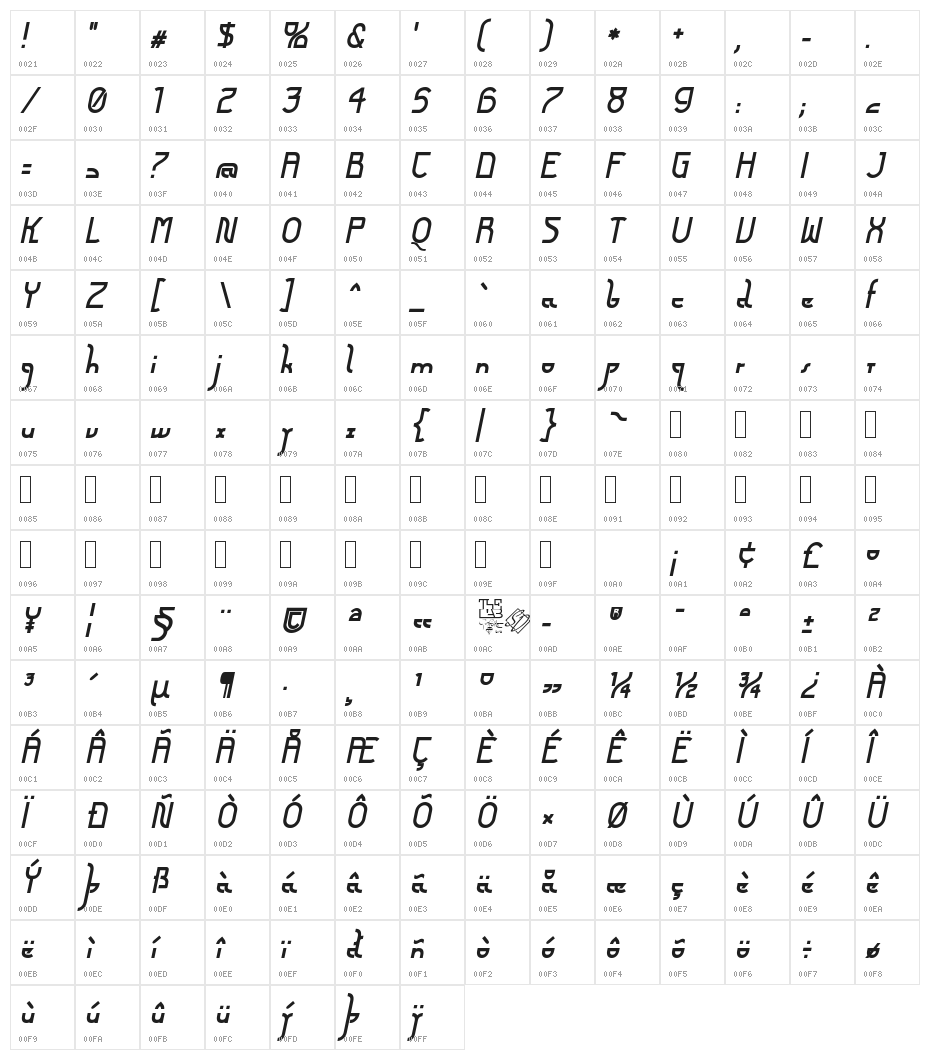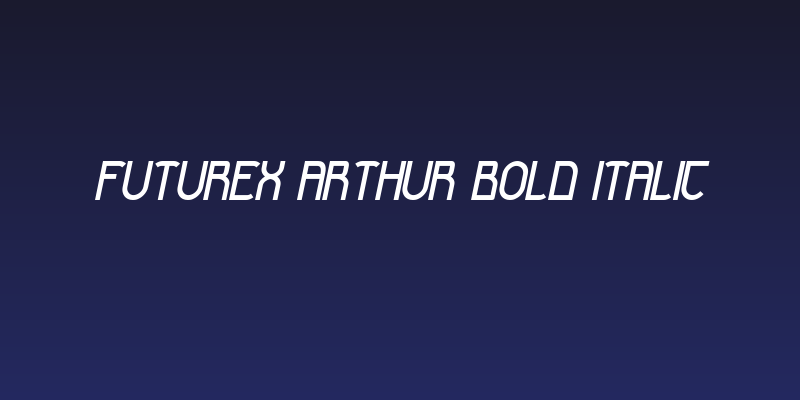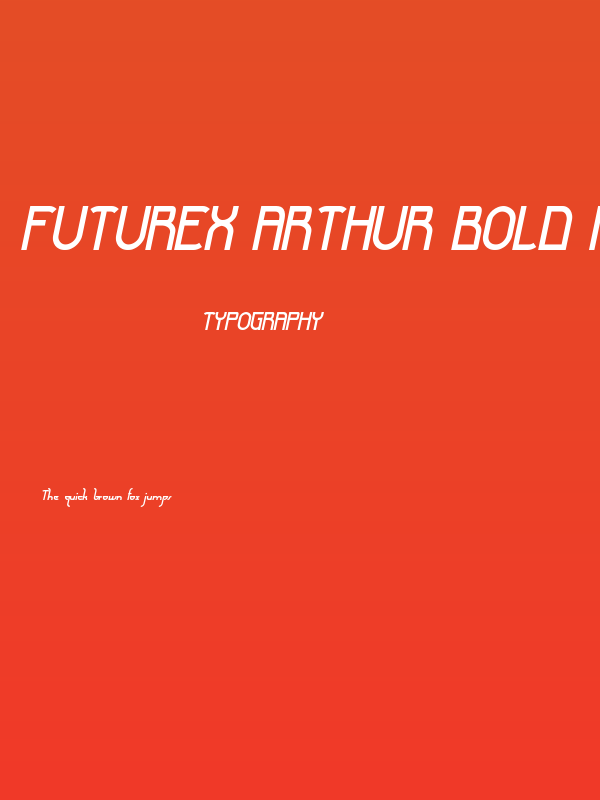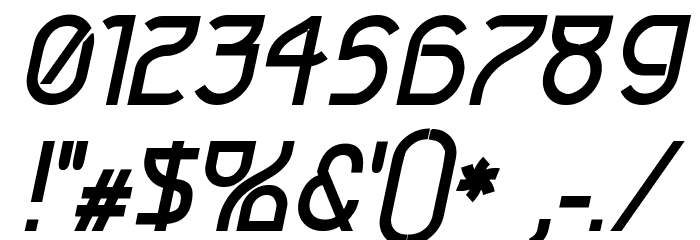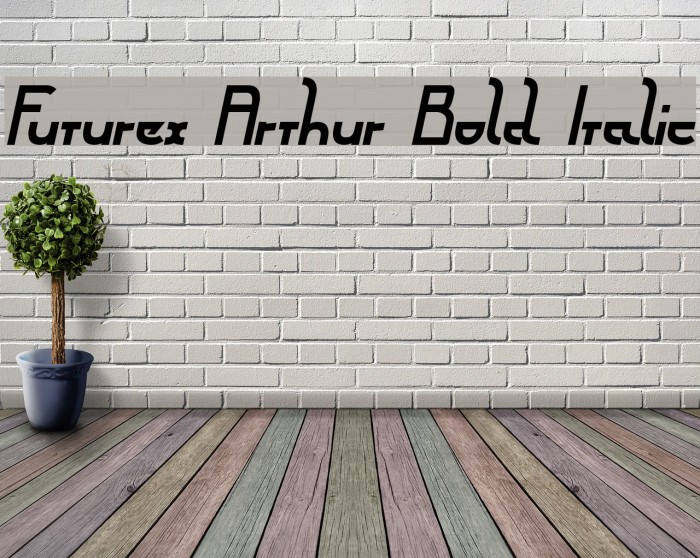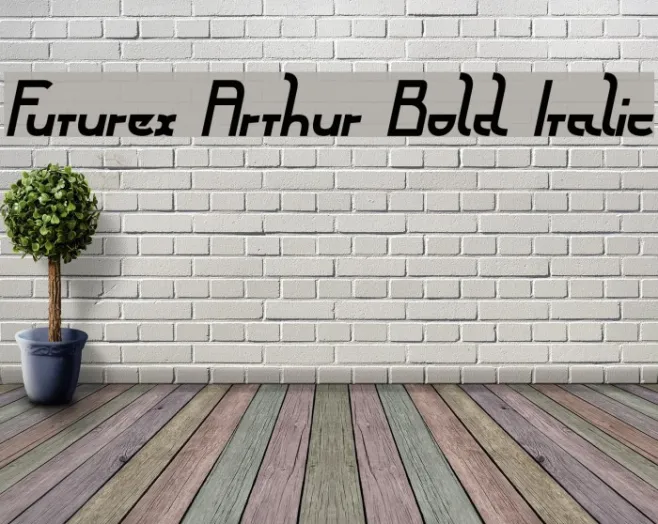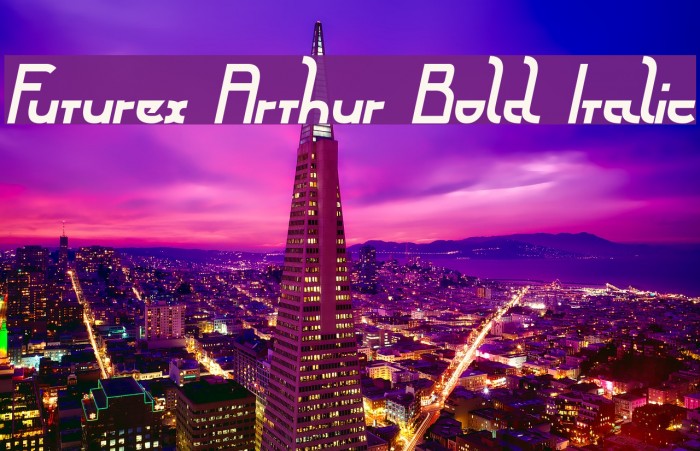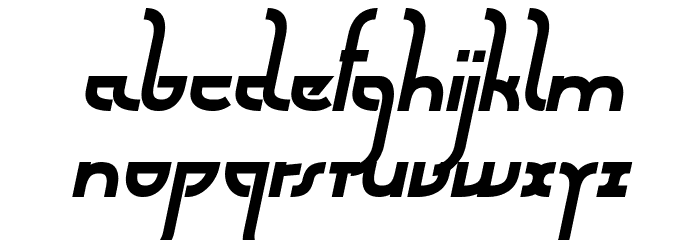
Futurex Arthur Bold Italic Font
| Style général | Futuristic |
| Projets proposés | Ideal for sci-fi themed projects, technology branding, video game titles, and modern advertising. |